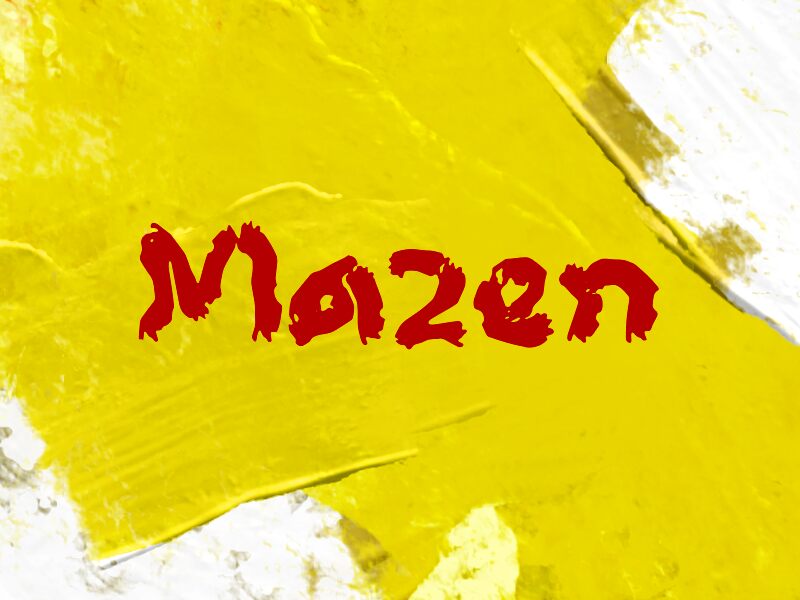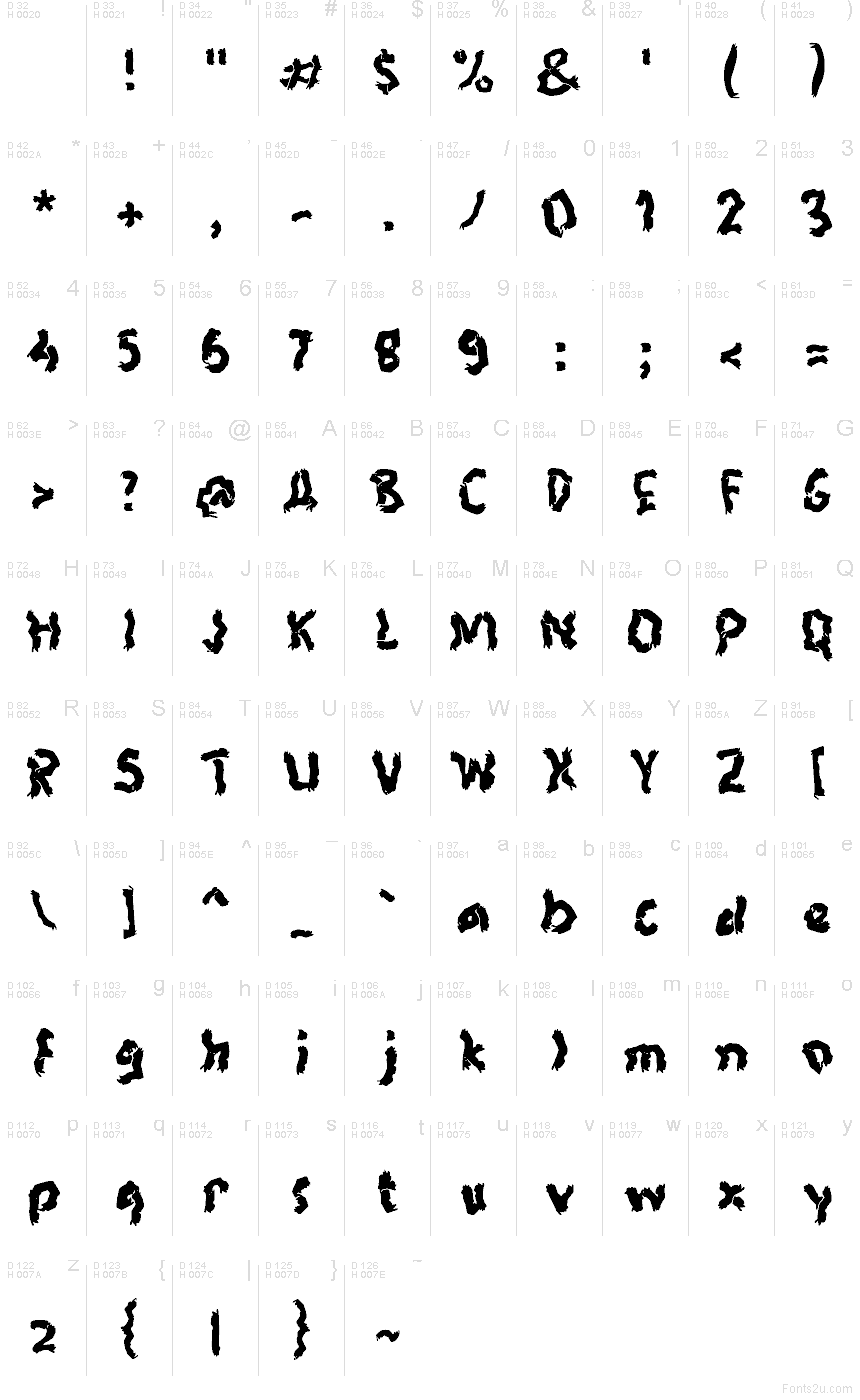
Mazen von Wep ist eine kostenlose Schriftart im „Trash Lettering“-Stil mit einer verschmierten, handgeschnittenen Optik. Sie wirkt eher wie Tinte, die durch nasse Farbe gezogen wurde, als wie eine saubere Zeichnung. Die Buchstaben wackeln und verklumpen auf unregelmäßige Weise, mit massiven Silhouetten, zerrissenen Kanten und hohlen Stellen, die der gesamten Schrift einen wilden, chaotischen Rhythmus verleihen.
Sie eignet sich perfekt für Poster, Album-Artworks, Zines, Horror-Flyer und rohe Streetwear-Grafiken, bei denen polierte Typografie zu kontrolliert wirken würde. Als kostenloser Font eignet sich Mazen auch hervorragend für kurze Überschriften, Titelkarten und Logo-Experimente, da die Buchstaben bereits genug Rauschen und Bewegung mitbringen, um den Großteil des Stylings für dich zu übernehmen.
Mazen